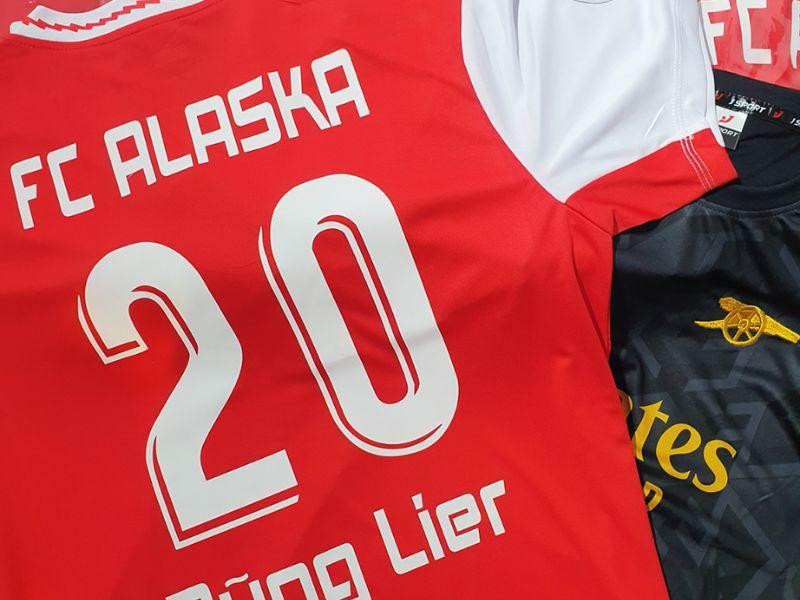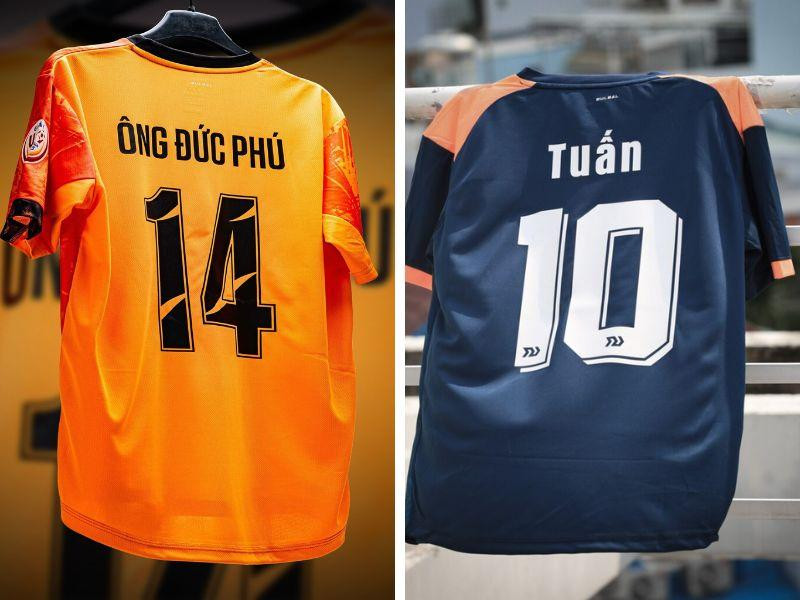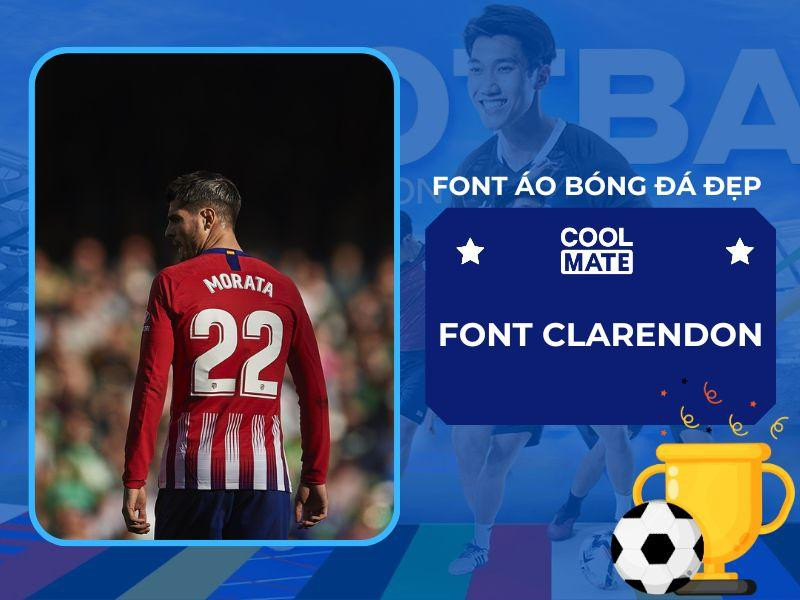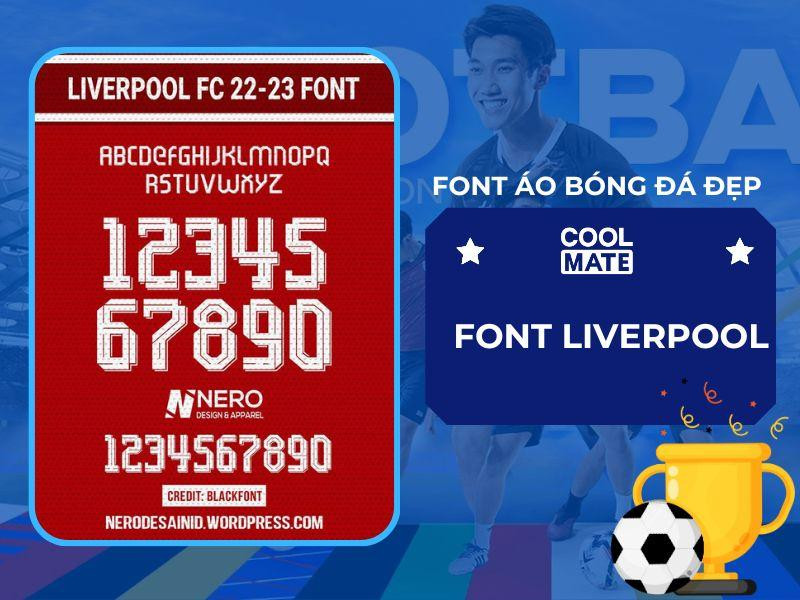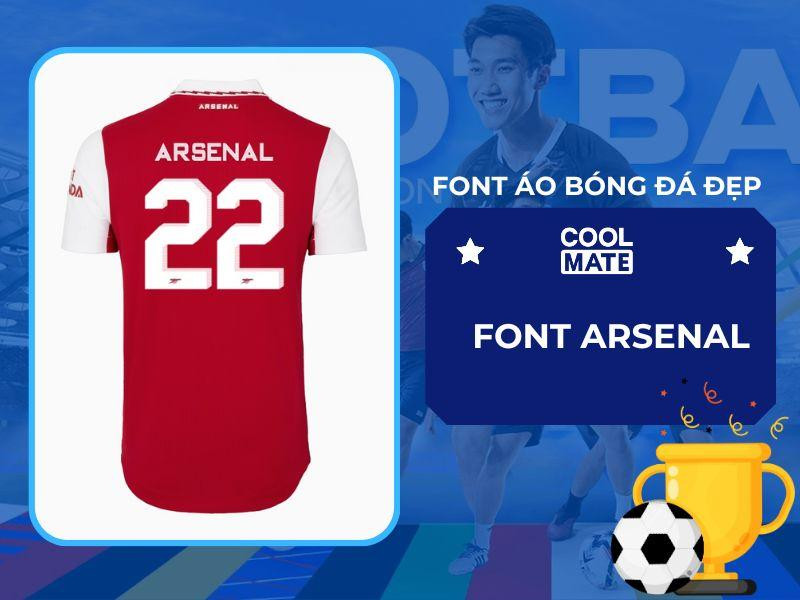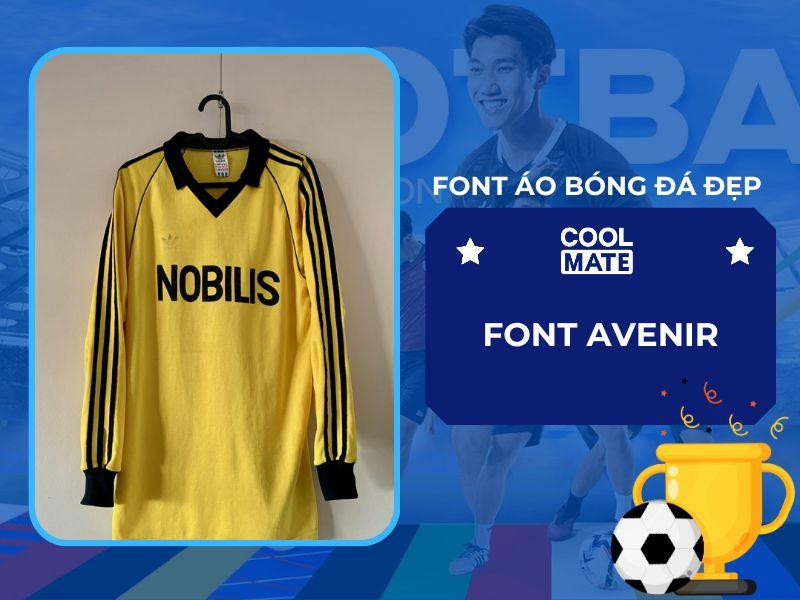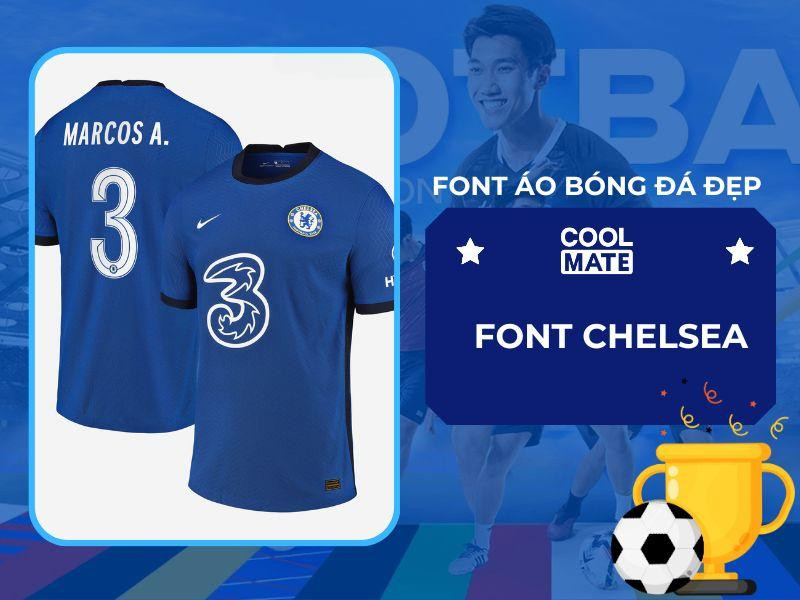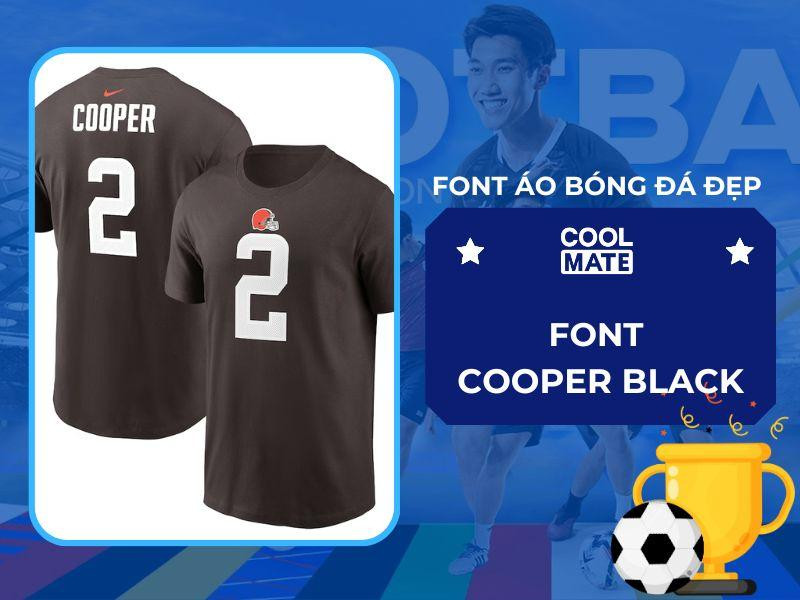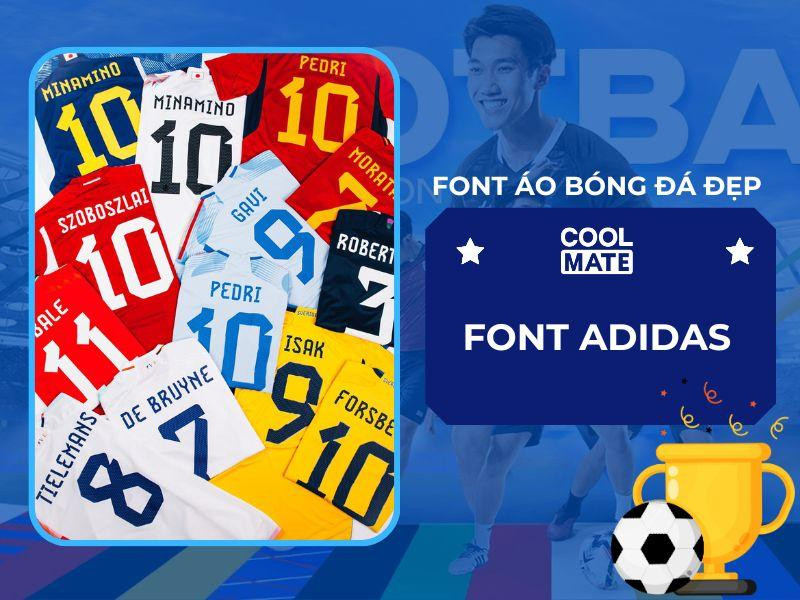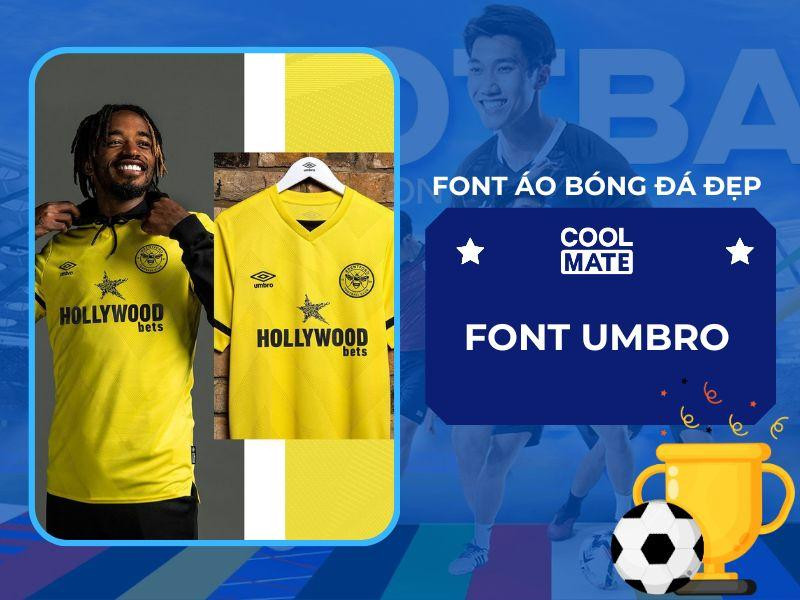
Font áo bóng đá đẹp: Từ các thương hiệu đến CLB nổi tiếng
Trong thế giới bóng đá đầy sôi động, chiếc áo đấu không chỉ là một bộ trang phục đơn thuần mà còn là biểu tượng mạnh mẽ của tinh thần đồng đội, bản sắc câu lạc bộ và niềm tự hào của người hâm mộ. Một yếu tố then chốt góp phần tạo nên vẻ đẹp và sự độc đáo của chiếc áo đấu chính là font áo bóng đá đẹp – kiểu chữ được sử dụng để in tên và số áo cầu thủ. Việc lựa chọn font chữ phù hợp có thể nâng tầm giá trị thẩm mỹ, gia tăng khả năng nhận diện đội bóng, và thậm chí còn truyền tải được phong cách chơi cũng như lịch sử của một câu lạc bộ. Bài viết này của chúng tôi sẽ đi sâu vào tầm quan trọng, các tiêu chí lựa chọn, và giới thiệu những mẫu font áo bóng đá đẹp, phổ biến nhất hiện nay, từ các thương hiệu thể thao hàng đầu cho đến những câu lạc bộ lừng danh thế giới, giúp bạn hiểu rõ hơn về ý nghĩa văn hóa và tầm quan trọng chiến lược của chúng trong làng túc cầu. Chọn được một mẫu font chữ ưng ý không chỉ thể hiện tính chuyên nghiệp mà còn khẳng định bản sắc riêng của đội bóng trên sân cỏ.
Tầm quan trọng của font chữ trên áo bóng đá
Font chữ trên áo bóng đá đóng vai trò cực kỳ quan trọng, vượt xa mục đích đơn thuần là hiển thị tên và số. Nó góp phần định hình bản sắc, tăng cường nhận diện và thậm chí là một phần của di sản văn hóa bóng đá. Việc lựa chọn một font chữ thích hợp không chỉ thể hiện sự chuyên nghiệp mà còn phản ánh tinh thần và triết lý của đội bóng.
Trước hết, font chữ là yếu tố nhận diện thương hiệu mạnh mẽ. Giống như logo hay màu sắc áo đấu, font chữ độc đáo giúp người hâm mộ dễ dàng nhận ra đội bóng của mình ngay từ cái nhìn đầu tiên. Các câu lạc bộ lớn thường đầu tư thiết kế font chữ riêng biệt, biến chúng thành một phần không thể thiếu trong bộ nhận diện thương hiệu. Điều này tạo nên sự khác biệt so với các đội bóng khác, khẳng định vị thế và lịch sử của câu lạc bộ. Một font chữ đặc trưng có thể trở thành biểu tượng, gắn liền với những khoảnh khắc lịch sử và thành công của đội bóng.
Thứ hai, font chữ cải thiện khả năng đọc và hiển thị. Trong một trận đấu diễn ra với tốc độ cao, từ khán đài hay qua màn hình tivi, việc số áo và tên cầu thủ phải rõ ràng, dễ đọc là điều tối cần thiết. Một font chữ được thiết kế tốt sẽ đảm bảo rằng thông tin này có thể được nhận biết nhanh chóng, giúp trọng tài, bình luận viên, và người hâm mộ theo dõi trận đấu một cách hiệu quả. Độ tương phản, kích thước, và khoảng cách giữa các ký tự đều là những yếu tố quan trọng cần được cân nhắc để tối ưu hóa khả năng đọc.
Thứ ba, font chữ mang ý nghĩa thẩm mỹ và thời trang. Áo bóng đá không chỉ là trang phục thi đấu mà còn là một sản phẩm thời trang được hàng triệu người hâm mộ trên thế giới mặc hàng ngày. Một font chữ đẹp mắt, hiện đại hoặc mang đậm tính cổ điển có thể tăng thêm sức hấp dẫn cho chiếc áo, biến nó thành một món đồ được khao khát. Sự hài hòa giữa font chữ và thiết kế tổng thể của áo đấu, từ màu sắc, hoa văn đến chất liệu, sẽ tạo nên một tổng thể hoàn chỉnh và thu hút.
Cuối cùng, font chữ có thể chứa đựng yếu tố lịch sử và văn hóa. Nhiều font chữ của các câu lạc bộ lâu đời được thiết kế dựa trên các yếu tố truyền thống, kiến trúc địa phương hoặc biểu tượng của thành phố. Việc duy trì và phát triển những font chữ này giúp bảo tồn và truyền tải giá trị lịch sử, kết nối người hâm mộ với quá khứ vinh quang của đội bóng. Nó không chỉ là một kiểu chữ mà còn là một phần của câu chuyện, một di sản được lưu truyền qua nhiều thế hệ.
Áo bóng đá in chữ số và tên cầu thủ đẹp mắt, thể hiện tinh thần đội bóngÁo bóng đá in chữ số và tên cầu thủ đẹp mắt, thể hiện tinh thần đội bóng
Các tiêu chí lựa chọn font áo bóng đá đẹp và hiệu quả
Việc lựa chọn một font áo bóng đá đẹp không chỉ dựa vào cảm quan cá nhân mà còn cần tuân thủ nhiều tiêu chí để đảm bảo tính thẩm mỹ, chức năng và giá trị truyền thông. Một font chữ tối ưu phải cân bằng được giữa sự độc đáo, dễ đọc và phù hợp với bản sắc của đội bóng.
Đầu tiên và quan trọng nhất là tính dễ đọc (legibility). Trên sân cỏ, đặc biệt là khi cầu thủ di chuyển nhanh, tên và số áo phải được nhận diện ngay lập tức từ nhiều góc độ và khoảng cách. Các font chữ quá phức tạp, có quá nhiều chi tiết hoặc quá mảnh sẽ gây khó khăn trong việc đọc. Font chữ cần có độ dày nét đủ, khoảng cách giữa các ký tự hợp lý và hình dáng rõ ràng để không bị lẫn lộn giữa các con số như “3” và “8”, hoặc “1” và “7”. Đây là yếu tố sống còn đảm bảo sự công bằng trong thi đấu và giúp người hâm mộ theo dõi trận đấu.
Thứ hai là sự phù hợp với bản sắc và thương hiệu của đội bóng. Mỗi câu lạc bộ đều có một câu chuyện, một lịch sử và một triết lý riêng. Font chữ được chọn nên phản ánh những yếu tố này. Một đội bóng có truyền thống lâu đời có thể chọn font chữ serif cổ điển, trong khi một đội bóng trẻ, năng động có thể ưu tiên các font sans-serif hiện đại, mạnh mẽ. Font chữ cũng nên hài hòa với logo, màu sắc và thiết kế tổng thể của áo đấu, tạo nên một hình ảnh nhất quán và chuyên nghiệp.
Thứ ba là tính bền vững và khả năng tương thích với công nghệ in ấn. Áo bóng đá thường phải chịu đựng cường độ giặt giũ và va đập cao. Font chữ cần được thiết kế sao cho khi in lên vải, các chi tiết không bị mờ nhòe, bong tróc hay biến dạng sau nhiều lần sử dụng. Các công nghệ in hiện đại như in decal nhiệt, in chuyển nhiệt hay in lụa đều có những đặc điểm riêng, và font chữ cần được tối ưu hóa để đạt hiệu quả tốt nhất với phương pháp in được lựa chọn, đảm bảo độ bền và sắc nét.
Thứ tư là tính độc đáo và khả năng tạo dấu ấn. Mặc dù cần tuân thủ các quy tắc về dễ đọc và phù hợp, một font chữ đẹp cũng cần có nét riêng để giúp đội bóng nổi bật. Việc sở hữu một font chữ độc quyền hoặc một biến thể được tùy chỉnh có thể tạo nên sự khác biệt đáng kể, trở thành điểm nhấn khó quên trong tâm trí người hâm mộ. Sự độc đáo này không nhất thiết phải quá phá cách mà có thể đến từ những chi tiết nhỏ, tinh tế trong đường nét hay góc cạnh của chữ.